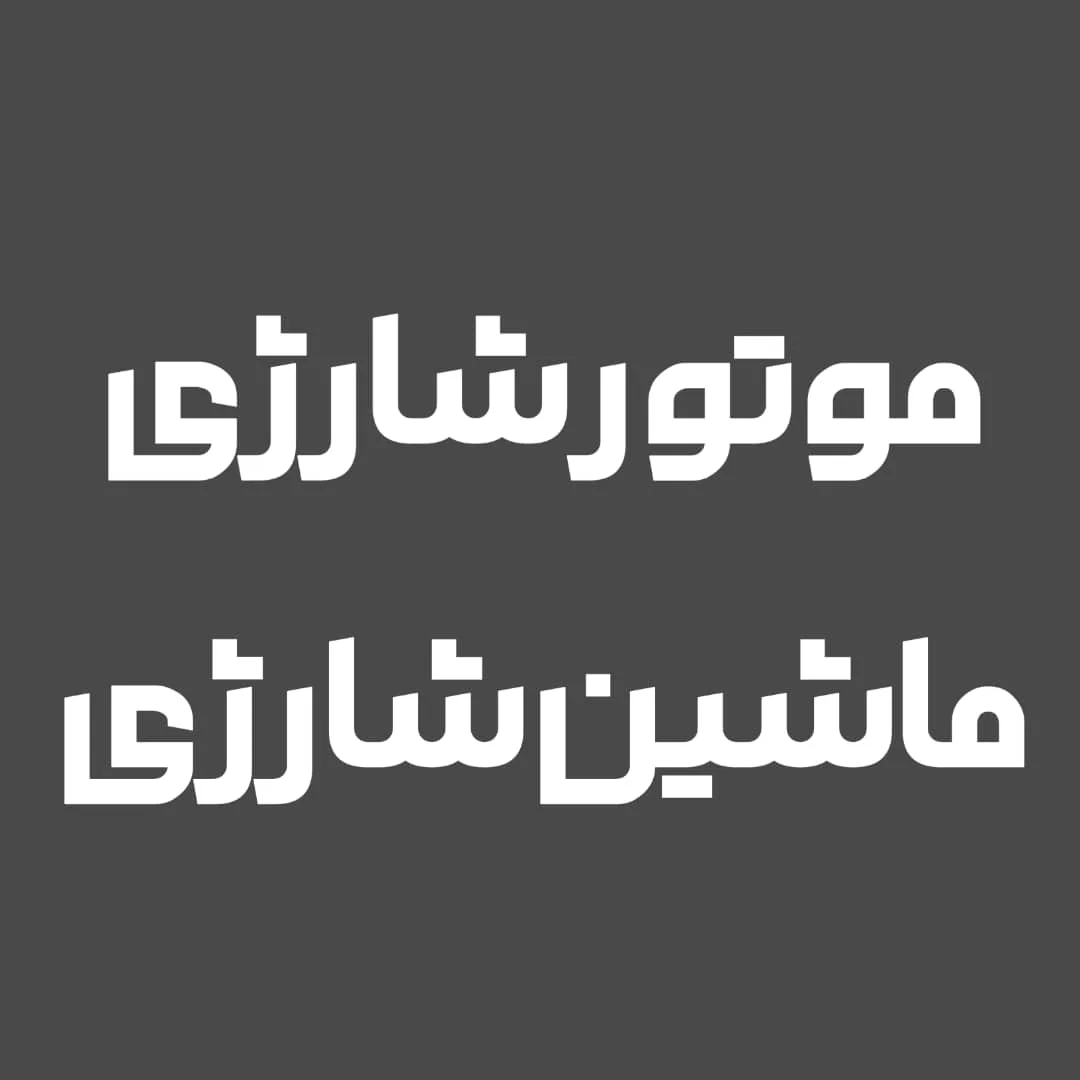
فونت چکمه از ایران فونت
تایپ فیس چکمه
طراح طراح فونت
دریا ابراهیمی
فونت چکمه ۲ بازسازی شده‌ی فونت چکمه۱ است که توسط سرکار خانم دریا ابراهیمی طراحی و اجرا شده است. فونت چکمه۱ در سال ۱۳۹۹ در یک وزن بولد و یک مدل نقطه گذاری دایره‌ای طراحی و توسط ایران فونت منتشر شد و در سال ۱۴۰۰ تمامی کاراکترها بازسازی شده و ۲ مدل نقطه گذاری جدید(مربع و مستطیل) اضافه شده است.
فونت چکمه از ایران فونت
تمامی حروف از جهت ارتفاع و اندازه یکسان شده و فاصله گذاری دقیق تر برای تک تک کاراکتر ها لحاظ شده است. اتصالات حروف برای هماهنگی یکسان کردن با یکدیگر بازسازی و تغییر کردند. فونت چکمه از سه زبان فارسی-عربی و انگلیسی پشتیبانی میکند و نقطه‌ی قوت آن داشتن حروف جایگزین است که نسبت به نسخه‌ی قبلی تغییرات بسیار زیادی داشته است. از فونت چکمه در طراحی عناوین-تیترها-متن های کوتاه-پوسترها-تراکت-کارت ویزیت و… میشود استفاده کرد. این فونت فقط در سایت ایران فونت قابل خریداری است و هیچ سایت یا شخصی حق فروش و یا پخش آن را ندارد.